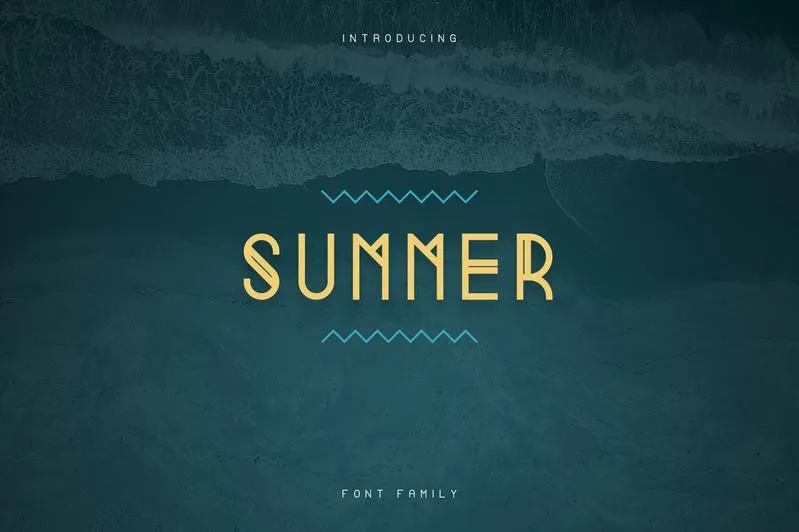
Summer Display Font – Free Demo – Download Grátis
A fonte Summer Display Font – Free Demo é uma opção ideal para designers buscando algo divertido e limpo para suas criações. Com 6 tipos diferentes e suporte a múltiplas línguas, este tipo de fonte oferece versatilidade incrível tanto em grandes como em pequenos tamanhos, tornando-a uma escolha perfeita para qualquer projeto visual. Ideal para criar designs chamativos ou mais elaborados que sejam igualmente agradáveis aos olhos, Summer Display Font – Free Demo não decepciona e traz um toque de diversão à sua próxima arte digital. Para designers brasileiros, essa fonte é uma escolha inteligente para quem busca um estilo moderno e funcional sem comprometer o equilíbrio entre simplicidade e detalhes.